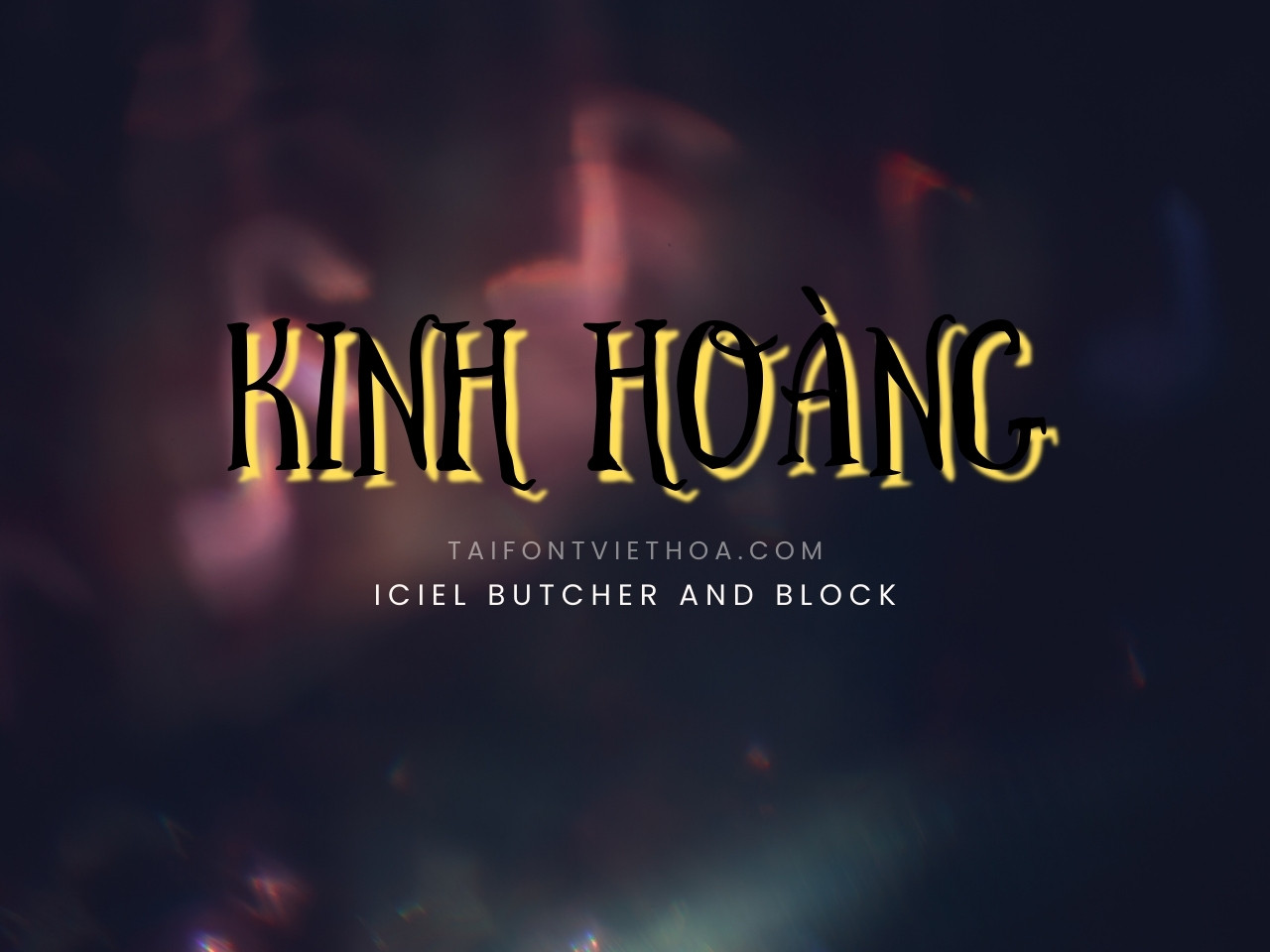
Giới thiệu về font iCiel Butcher And Block – Cá tính, thủ công và mang hơi thở cổ điển
iCiel Butcher And Block là một kiểu font viết tay pha lẫn phong cách thủ công (handcrafted display), mang đậm tinh thần cổ điển và nam tính. Được thiết kế với cảm hứng từ những bảng hiệu quán ăn kiểu Mỹ hoặc bao bì sản phẩm retro, font mang đến sự chắc chắn, dày dặn và cá tính mạnh mẽ. Phiên bản Việt hóa được iCiel thực hiện chỉnh chu, hỗ trợ đầy đủ tiếng Việt cùng hơn 60 ngôn ngữ phổ biến khác, giúp font có thể áp dụng linh hoạt trong nhiều lĩnh vực thiết kế.
Font đã được taifontviethoa.com chọn lọc và giới thiệu đến cộng đồng như một lựa chọn lý tưởng cho các dự án cần điểm nhấn typography đậm nét, mang chất thủ công, cổ điển hoặc cá tính mạnh. Sự kết hợp giữa kiểu dáng cứng cáp và nét viết tay tự nhiên tạo nên một diện mạo độc đáo cho thiết kế thương hiệu, thực phẩm, bảng hiệu hoặc in ấn bao bì mang đậm phong cách cá nhân.
Đặc điểm thiết kế và ứng dụng nổi bật của font iCiel Butcher And Block
iCiel Butcher And Block có nét chữ in hoa mạnh mẽ, với các chi tiết góc cạnh dày bản nhưng vẫn giữ sự mềm mại nhờ hiệu ứng viết tay. Thiết kế hướng tới cảm giác thủ công, mộc mạc và đậm chất retro. Font sử dụng đường nét gãy gọn, độ dày đồng đều và khoảng cách chữ cân đối, lý tưởng cho những tiêu đề nổi bật hoặc logo đặc thù.
Font phù hợp cho các ngành nghề như ẩm thực, nhà hàng, cafe, quán bar, thiết kế bao bì sản phẩm thủ công, branding đồ ăn hoặc dịch vụ mang phong cách cổ điển. Các ứng dụng tiêu biểu gồm: thiết kế bảng hiệu vintage, bao bì thực phẩm, logo quán ăn, poster sự kiện, thiết kế menu hoặc các chiến dịch branding mang tính lễ hội, sinh nhật, Trung thu, Giáng sinh.